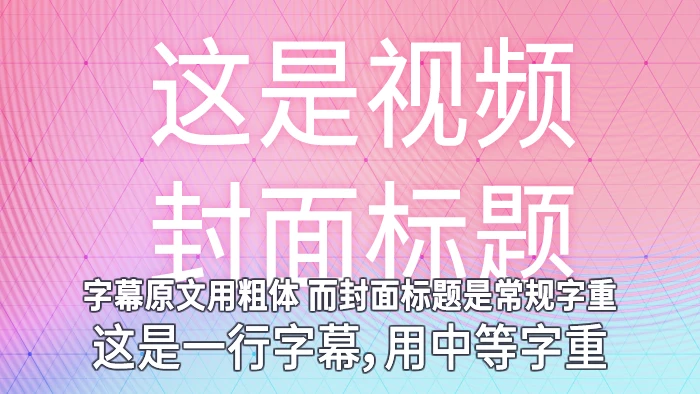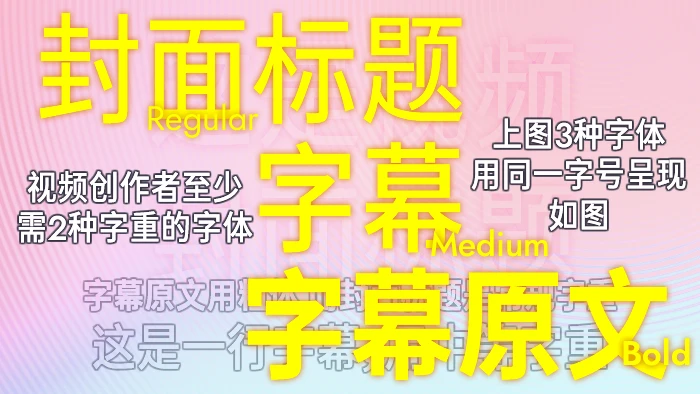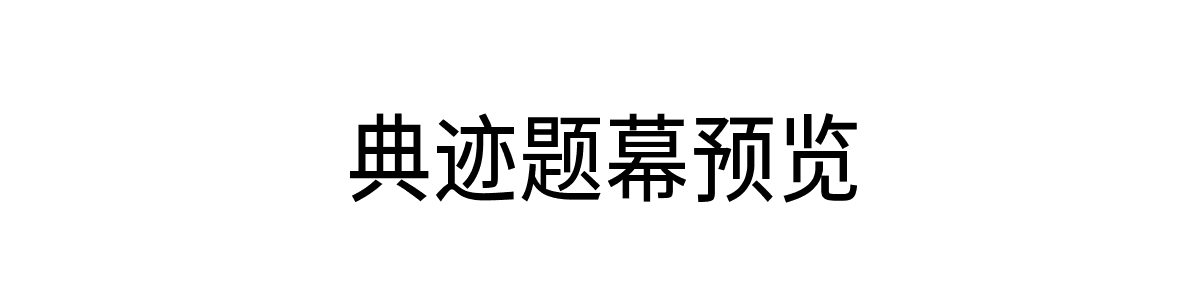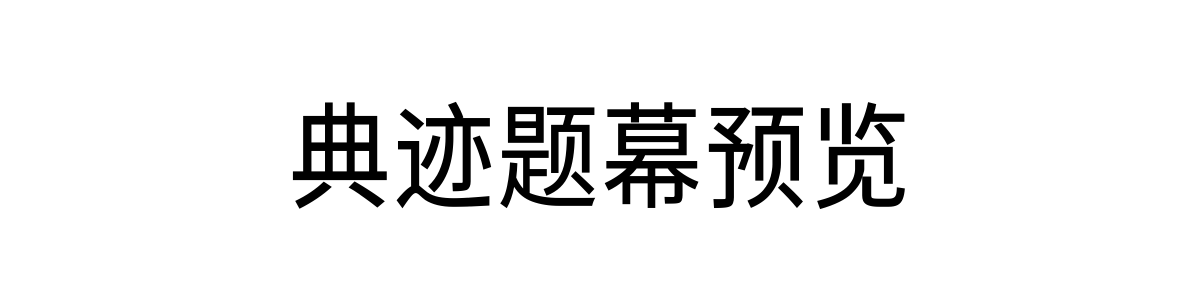
典迹题幕
典迹题幕(MonuTitl)是一款专门面向横排标题与字幕场景使用的女书窄黑体,名称里的 “Titl” 取自 subtitle,也直接点明了它的核心用途。
一共提供三种字重,分别是窄体宜读、窄体中粗和窄体粗体,其中窄体宜读的粗细大致等同于常规体。之所以做成窄身形态,主要是考虑到标题和字幕大多要求一行显示、不轻易换行,更紧凑的字形能在一行内容纳更多文字。
字体风格
典迹题幕整体为现代窄黑体造型,字形紧凑利落,识别度高,三种字重层次分明。风格简洁中性,没有多余装饰,既满足字幕远距离阅读需求,又适合作为标题使用,兼顾实用性与通用性。